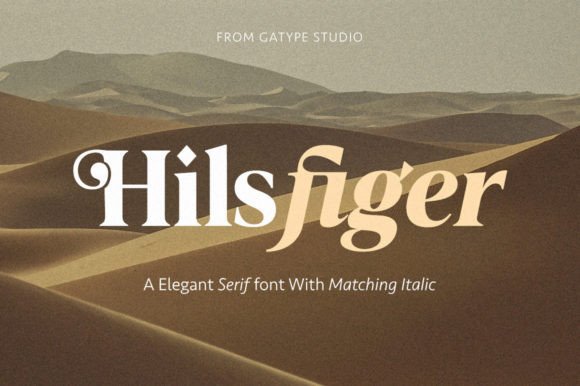
Hilsfiger
Jika Anda mencari aset berkualitas tinggi seperti Hilsfiger, paket premium ini adalah pilihan fantastis untuk proyek kreatif Anda.
Dibuat dengan presisi, Hilsfiger menyediakan vektor yang bersih, tipografi yang halus, serta lisensi komersial untuk ketenangan pikiran Anda.
Baik Anda membuat produk POD (Print on Demand), undangan pernikahan, atau grafis media sosial, Hilsfiger adalah pilihan yang sangat ideal.